今回は、Peter Dawson 著、手嶋由美子翻訳の『街で出会った欧文書体実例集 -THE FIELD GUIDE TO TYPOGRAPHY-』をご紹介します。
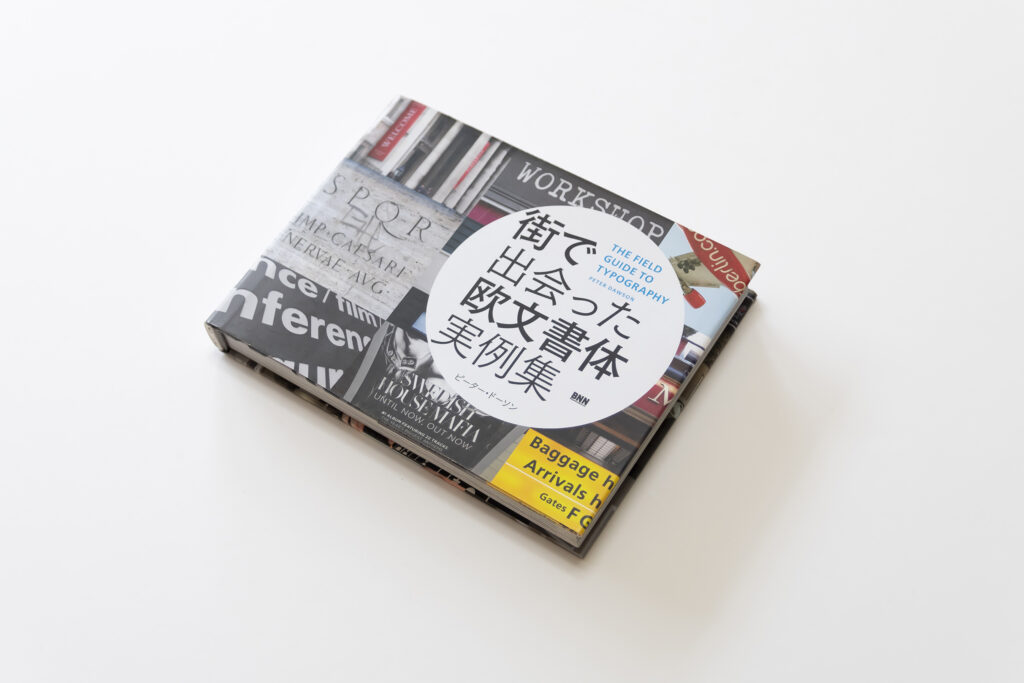
約120の欧文書体の概要と実際の使用例写真、同カテゴリー書体の比較解説がまとめられています。300ページ越えとボリューミーですが、基本的に1書体1見開きなのでまずは気になる書体だけでも気軽に読めるのが嬉しい一冊です。
欧文書体のことを知りたいけど取っ掛かりを掴みかねているという方には特にオススメです。組版を眺めるだけでは分からない、それぞれの書体を取り巻くストーリーがこの本では紹介されています。似たように見えていた書体もこの本を読んだ後は個性が際立って見えてくるのではないでしょうか。分類・制作年・デザイナーなどの基礎情報も充実しているので、もっとその書体のことを調べたい時にも役立つと思います。
『街で出会った欧文書体実例集 -THE FIELD GUIDE TO TYPOGRAPHY-』